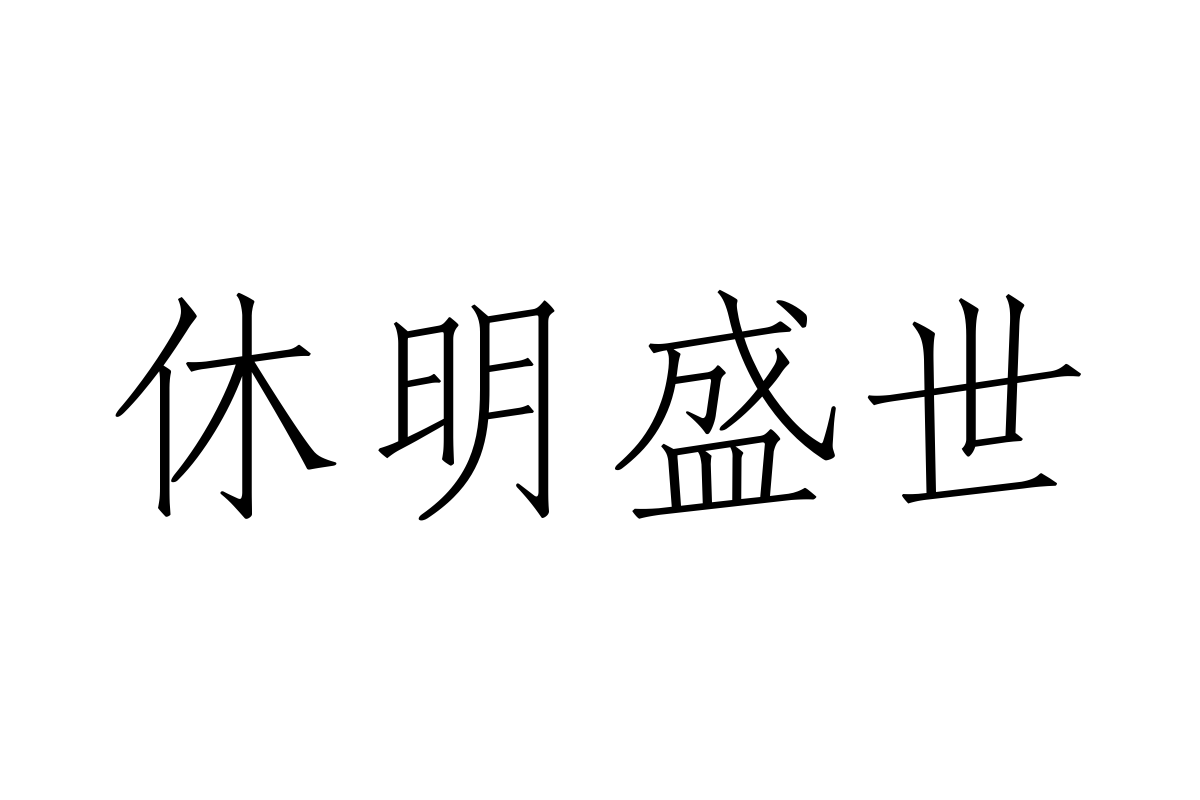
汉仪浙风宋朝繁体字体是一款具有浓郁中国古典风格的字体,它源自于宋朝的书法艺术。这款字体的设计灵感来源于宋代的书法风格,线条流畅,结构严谨,给人一种古朴典雅的感觉。
汉仪浙风宋朝繁体字体的特点主要体现在以下几个方面:
1. 字形结构:这款字体的字形结构独特,笔画粗细适中,线条流畅,既有力度又有柔美,给人一种古朴典雅的感觉。
2. 字体风格:汉仪浙风宋朝繁体字体的风格独特,线条流畅,结构严谨,给人一种古朴典雅的感觉。
3. 字体表现:这款字体在表现上非常出色,无论是在正式场合还是在日常使用中,都能展现出其独特的魅力。
4. 适用场景:汉仪浙风宋朝繁体字体适用于各种需要展现中国古典风格的场合,如设计、印刷、包装等。
总的来说,汉仪浙风宋朝繁体字体是一款具有浓郁中国古典风格的字体,它能够很好地展现出宋代书法的艺术魅力,适合用于各种需要展现中国古典风格的场合。